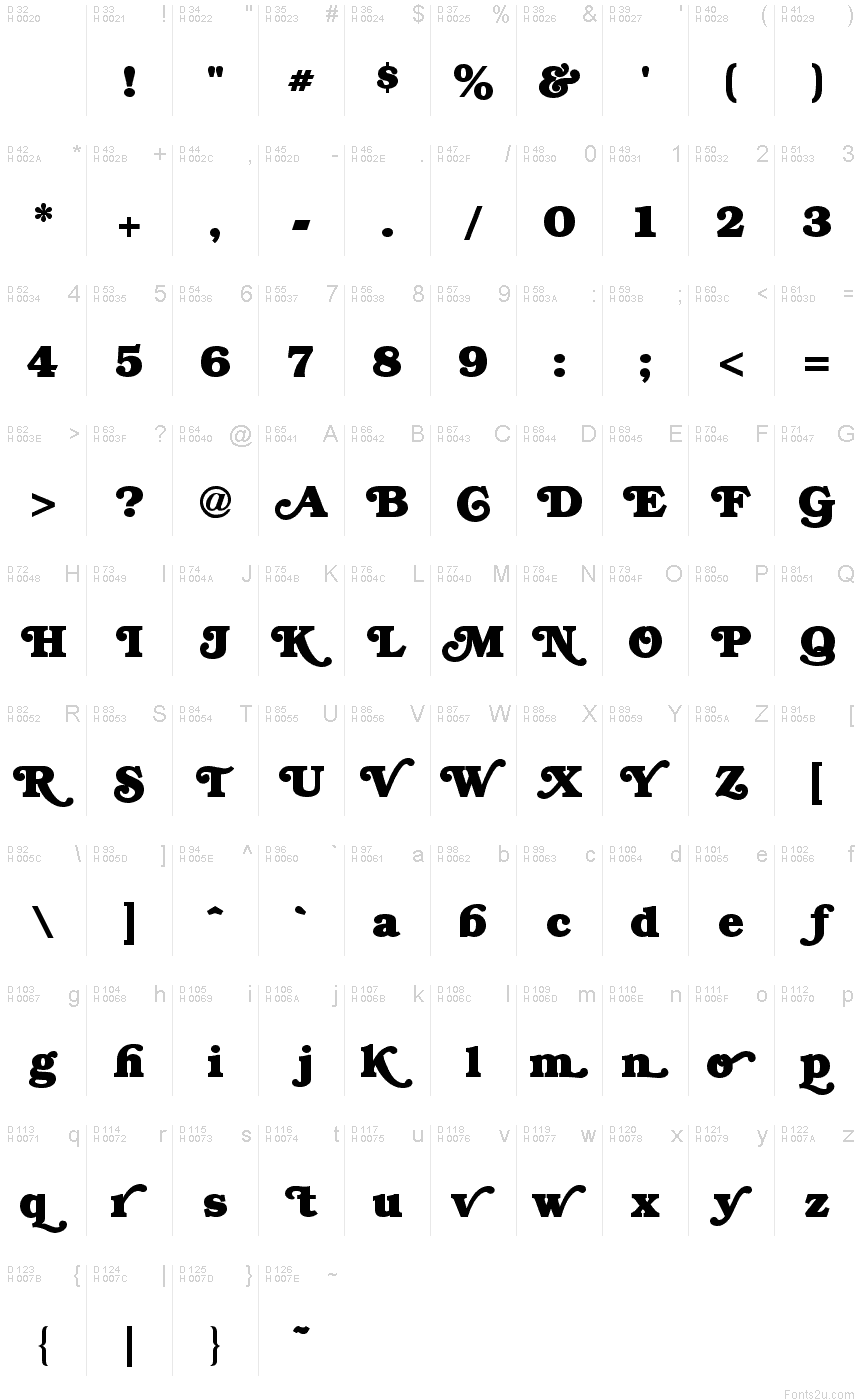
Swash  Normal
Swash to darmowy, ozdobny krój pisma typu display z żywym, retro klimatem, idealny do nagłówków. Litery są duże, ciężkie i teatralne – łączą masywne, blokowe kształty z przerysowanymi zawijasami, haczykowatymi końcówkami i drobnymi nacięciami, dzięki którym font przypomina typografię z cyrkowych plakatów lub unikalne drewniane czcionki.
Świetnie sprawdzi się na plakatach, szyldach, ulotkach, opakowaniach, kartach tytułowych i krótkich nagłówkach, gdzie jedno słowo ma tworzyć cały nastrój. Jako darmowy font, Swash najlepiej prezentuje się w krótkich formach, takich jak monogramy czy inicjały, ponieważ jego szerokie kształty i dekoracyjne wygięcia dodają charakteru nawet zaledwie kilku literom.